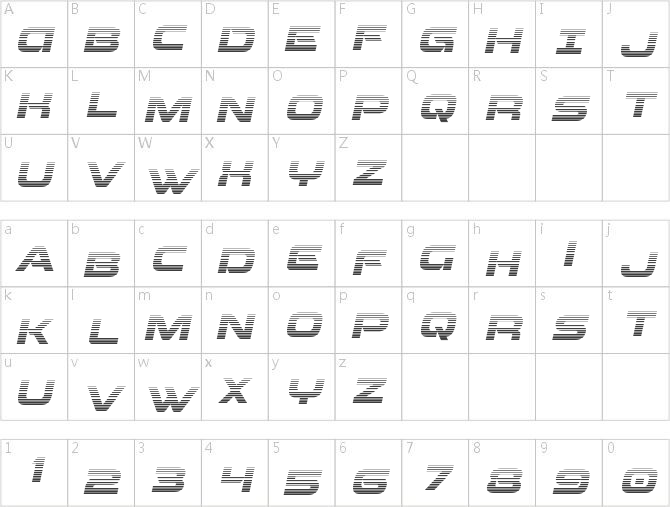
Beam Weapon Gradient Italic
Beam Weapon Gradient Italic介绍
Beam Weapon Gradient Italic字体字库是一款让人赏心悦目、百看不厌的英文字体,适合各类广告和产品包装设计应用,字体大小0.07MB,格式为ttf字体,上传用户是wo~,作者/版权方为未知